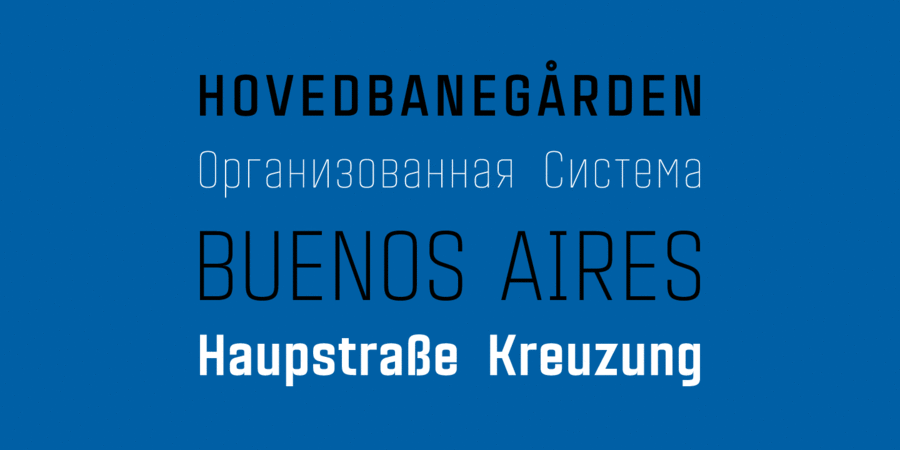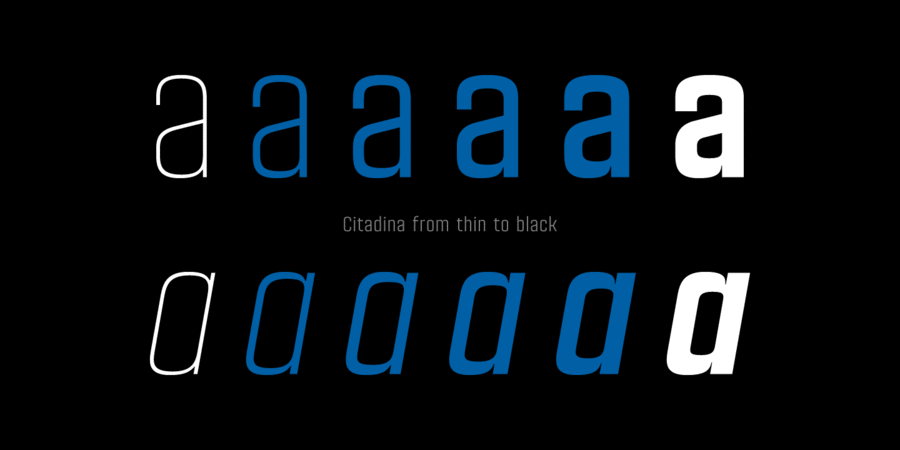
Citadina (12 шрифтів)
Опис гарнітури CitadinaГарнітура Citadina – це модульний гротеск з геометричним, механічним, нейтральним виглядом. Шрифт трохи стиснений, що робить його особливо ефективним для економії місця. Він був задуманий для коротких і середніх текстових блоків, а також для заголовків будь-якого розміру. Citadina складається з 12 накреслень. Кожне містить гліфи для латиниці й кирилиці, а також капітель та лігатури. Шрифт розробив Пабло Балселлс в 2016 році.
Особливості сімейства шрифтів CitadinaХіт десятиліття:
Хіт 2010-х Citadina підтримує 83 мовиУкраїнська, Англійська, Німецька, Польська, Португальська, Іспанська, Французька, Російська, Чеська, Голландська, Італійська, Шведська, Турецька, Фінська, Білоруська, Сербська, Болгарська, Естонська, Литовська, Албанська, Африкаанс, Баскська, Бретонська, Валенсаска, Galician, Гельська (Шотландська), Данська, Індонезійська, Ірландська, Ісландська (Win), Каракалпацька, Каталонська, Норвезька, Окситанська, Ретороманська, Самі Лулі, Тсванська, Узбецька (Лат.), Фарерська, фризька, Чаморро, Естонська (Win), Південносаамська, Албанська (Win), Угорська, Верхньолужицька, Карельська, Латвійська (Mac), Литовська (Mac), Маорійські (Mac), Молдавська (Лат.), Нижньолужицька, Румунська (Win), Словацька, Словенська, Туркменська (Лат.), Хорватська (Win), Естонська (Mac), Курдська, Латишська, Маорійські, Руминська, Абазинська, Аварська, Агульська, Адигейська, Даргинську, Інгуську, Кабардино-Черкеська, Кабардинська, Карачаєво-Балкарська, Кумицька, Лакська, Лезгинська, Македонську, Мордовсько-Мокшанська, Мордовсько-Ерзянська, Ногайська, Рутульська, Табасаранська, Татська, Цахурська, Чеченська Функції сімейства шрифтів CitadinaЗастосування гарнітури у верстці:
Асоціації з сімейством шрифтів CitadinaОсобистість і характер гарнітури:
неоновий, точний, футуристичний, рівний, прямокутний, тонкий, статичний, логічний, холодний, легкий, міський, сучасний, інженерний, урбаністичний, креслярський, скляний, крихкий, прозорий, дротяний, спокійний, худий, стійкий, космічний, машинний, гострий, чіткий, різкий, стабільний, твердий, серйозний, техногенний, практичний, прагматичний, технічний, якісний, міцний, надійний, впевнений, переконливий, сильний, індустріальний, крутий, амбітний, гучний, важливий, відповідальний, наполегливий, суворий, важкий, сталевий, залізний, гарячий, монументальний
фантастика, гаджет, девайс, креслення, архітектура, інженер, Місто, електроніка, прилад, айтішник, айті, IT, технології, космос, дизайн, техніка, конструктор, автоматика, гра, авто, шутер, екшен, промисловість, верстат, інструмент, електростанція, енергетика, завод, тренажери, ремонт, блокбастер, бойовик, Футбол, селфі, кінотеатр, спорт, паливо, кіно, комп'ютерна гра, нафта Гарнітура асоціюється з віком: